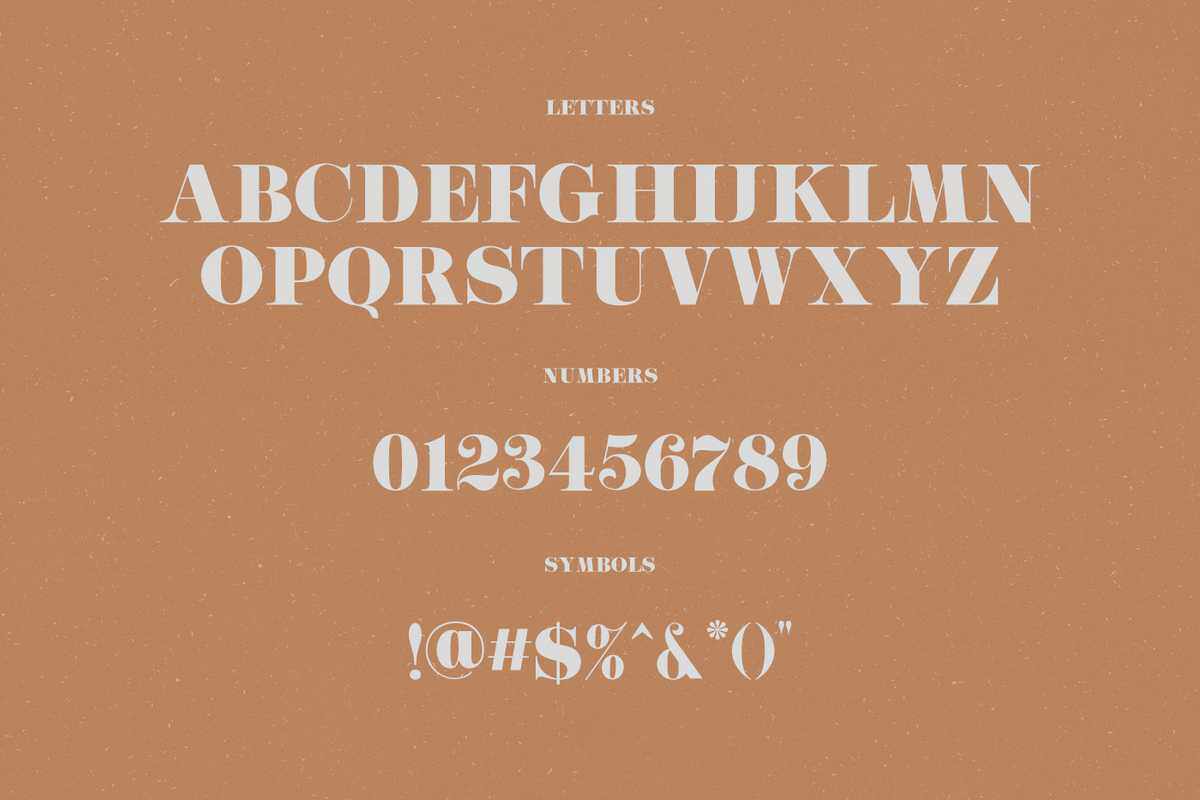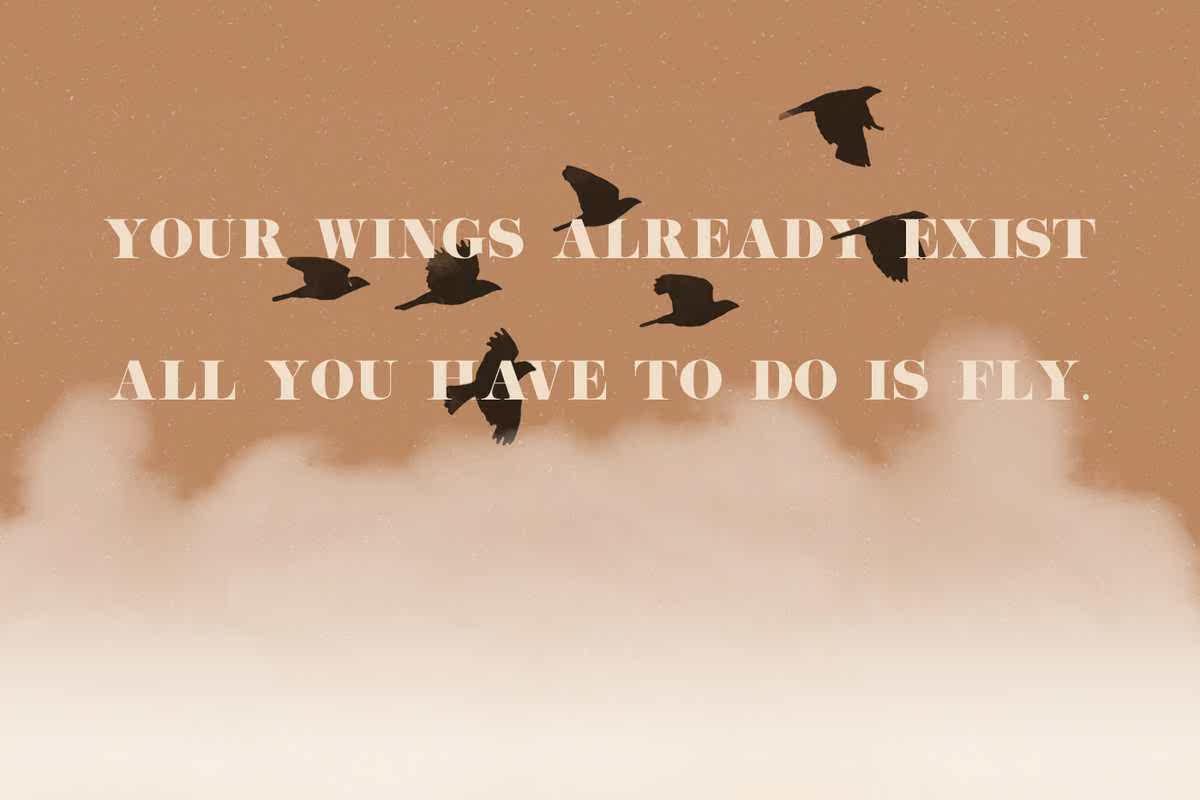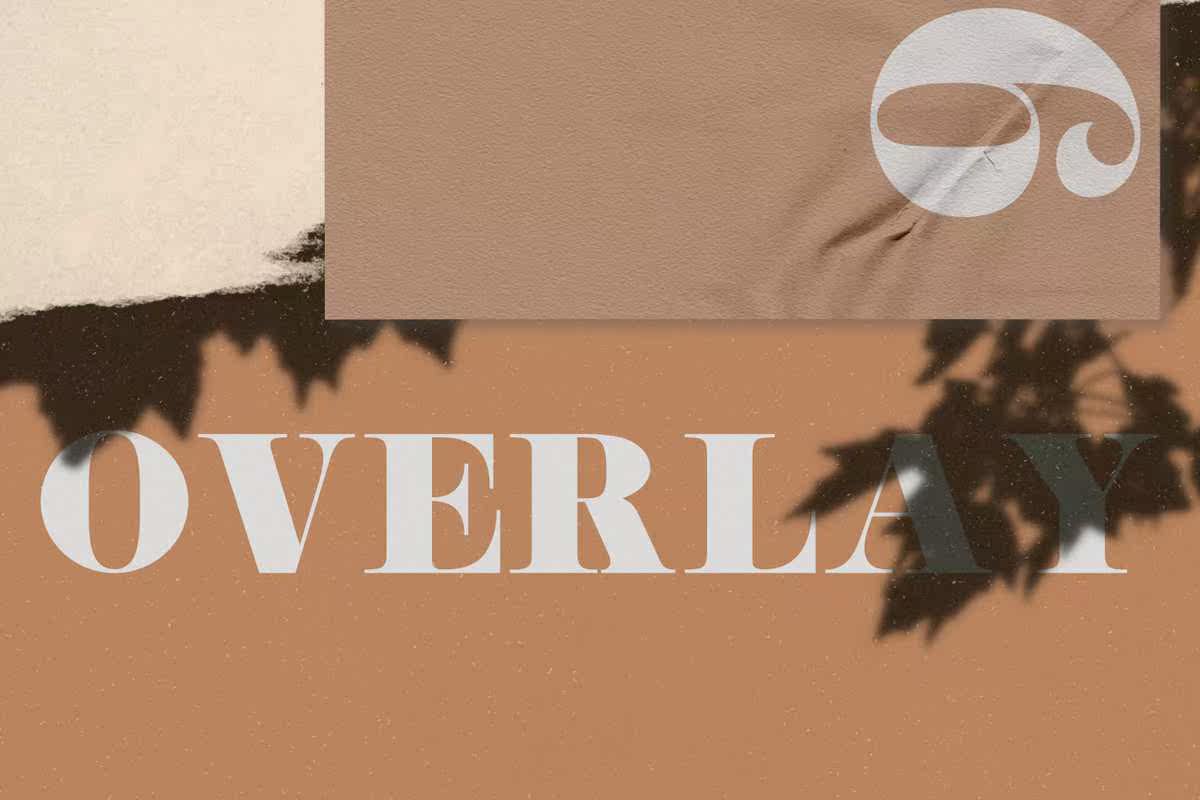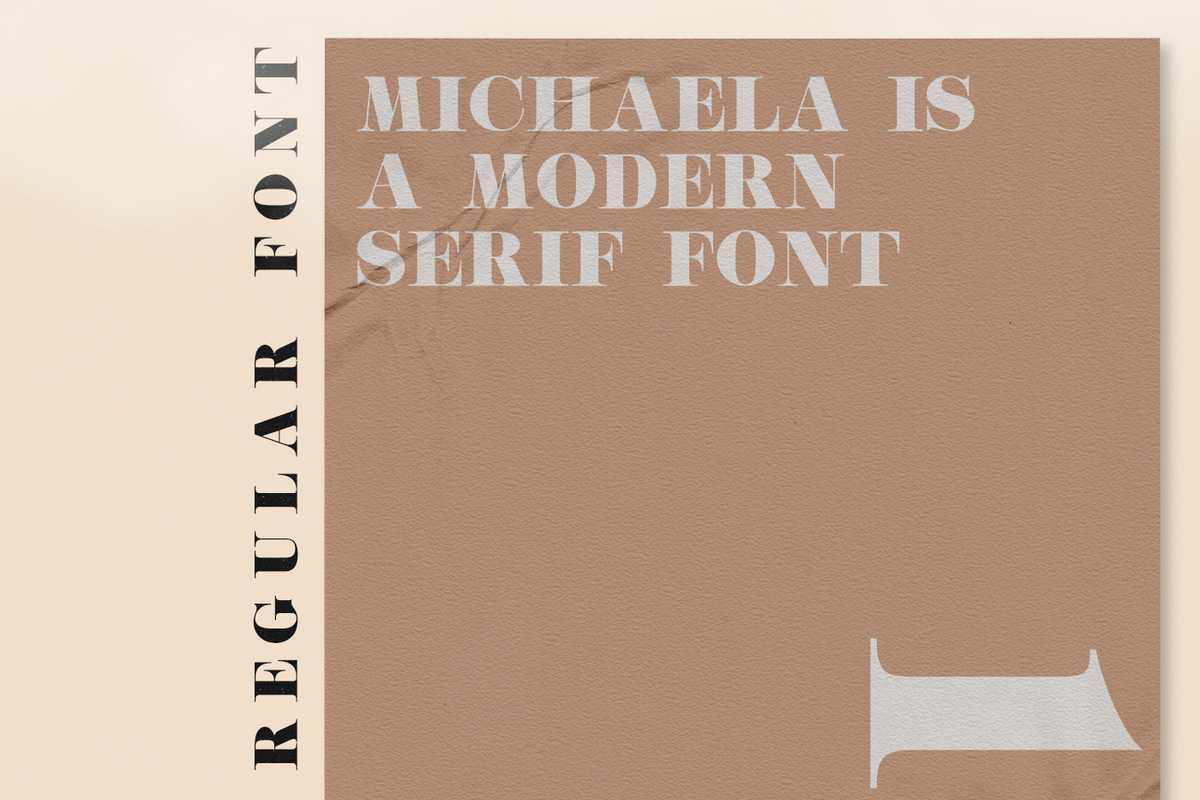
Michaeslaismodernserifont.madefornyProfessionalProjectBranding。它最适合于品牌、印刷、婚礼和报价。Michaelao提供了许多应用于许多图形或编辑项目的可能性。每个项目都有一个独立的BeautifUltouch.Michaeslaismodernserifont.madeforyProfessionalProjectBranding。它最适合于品牌、印刷、,Wedding and Quotes.Michaelao提供了许多应用于许多图形编辑项目的可能性。每个项目都有自己的独特之处。